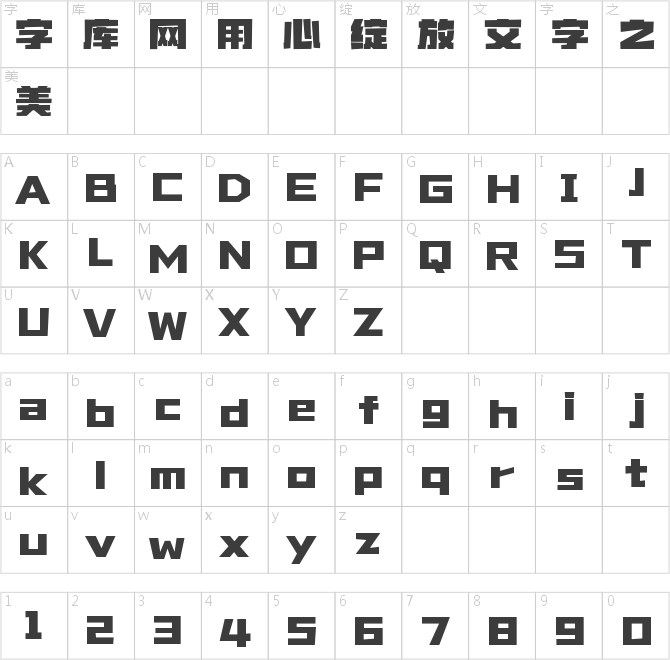
山海機(jī)甲超黑
山海機(jī)甲超黑,是一款綜藝標(biāo)題黑體字體,包含簡體漢字6763個(gè)。該字體是一款具有強(qiáng)勁視覺沖擊力的綜藝風(fēng)格標(biāo)題字體。字形寬大扁平,充實(shí)填滿整個(gè)字框,造型硬朗,全直線的筆畫構(gòu)成棱角分明、堅(jiān)實(shí)有力。